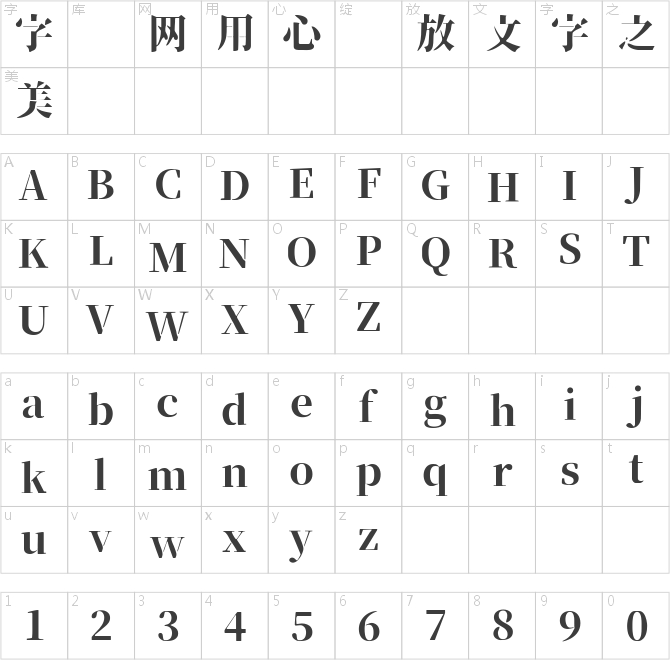
字體名稱: 裝甲明朝
裝甲明朝
由日本網(wǎng)友從開源字體「思源宋體」改版而來,基于SIL Open Font License 1.1協(xié)議,但最終出來的效果卻不大一樣,裝甲明朝體,將水平橫線筆劃修改得超細(xì),在文字表現(xiàn)上,顯得張力更強(qiáng),十分霸氣。 英文名稱:Soukou Mincho